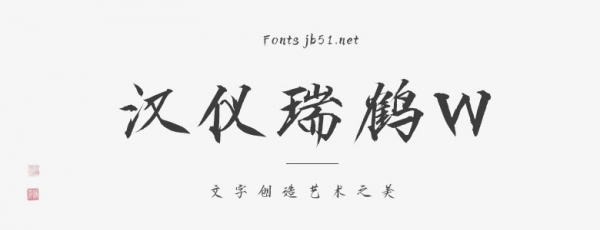
漢儀瑞鶴由漢儀簽約設(shè)計(jì)師劉輝設(shè)計(jì)的一款手寫(xiě)體。這款字來(lái)源于宋徽宗的“瘦金書(shū)”,設(shè)計(jì)師將其在設(shè)計(jì)行業(yè)深耕的經(jīng)驗(yàn)與多年的書(shū)法研習(xí)經(jīng)驗(yàn)相結(jié)合,創(chuàng)作出了這款蘊(yùn)新于古的漢儀瑞鶴。,適合于文化類的宣傳設(shè)計(jì)、商業(yè)類品牌的廣告和產(chǎn)品包裝設(shè)計(jì)以及個(gè)性化文字排版等較多場(chǎng)景。